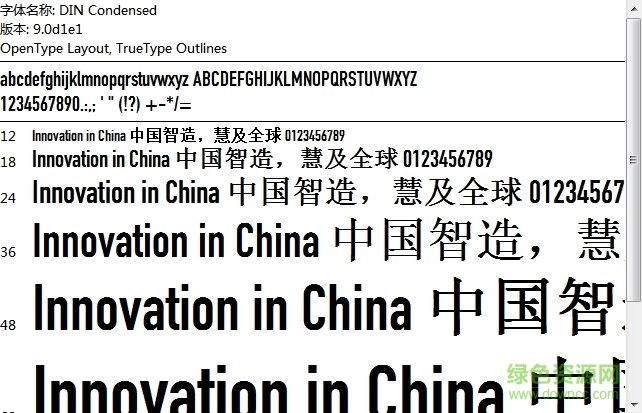
dincondensedbold字體是一款使用較為方便的英文字體,是DIN字體系列的黑體字體,整體結(jié)構(gòu)疏密相間,即給人清晰直觀的視覺(jué)體驗(yàn),還不會(huì)帶來(lái)壓抑之感,喜歡的朋友就來(lái)綠色資源網(wǎng)體驗(yàn)吧!
DIN Condensed Bold
dincondensed-bold是一款支持ios、Android等系統(tǒng)的藝術(shù)設(shè)計(jì)字體,給你的英文內(nèi)容更加的美觀簡(jiǎn)潔,讓你的作品更加飽滿。